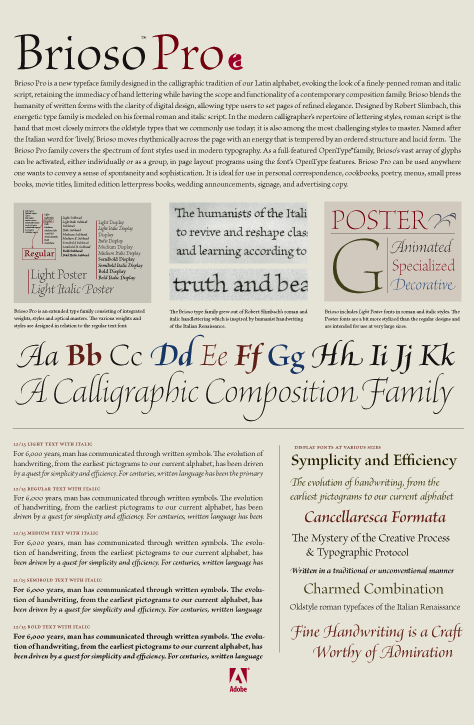
Brioso
Pro |
Robert Slimbach (Illinois, 1956 -)
Este typeface designer, ex-director artístico do Departamento de type design da Adobe, fez poucas criações verdadeiramente originais, mas produziu uma série de famílias de grande sucesso: Adobe Garamond, Myriad, BriosoSlimbach trabalhou na Adobe Systems em San José,
California. Durante a sua actividade na Adobe, Slimbach visitou o
A Brioso Pro é sem dúvida um ponto alto na carreira de Robert Slimbach. Desde que começou «a fazer letras» na década de 1980, Slimbach mostrou forte afinidade com as letras humanistas, caligrafadas ou não; basta ver a Poetica Chancery, a Clafisch Script e a San Vito.
Na Brioso Pro, Bob Slimbach integrou toda a sua perícia e os aprofundados estudos da caligrafia humanista da Renascença italiana (ver exemplo em baixo). Deste esforço resultou uma fonte de nítida inspiração caligráfica. As itálicas (normais e Swash) estão admiravelmente integradas nesta extensa família, apta a satisfazer as exigências de qualquer profissional do desenho gráfico. Faz parte dos requintes da Brioso a escolha entre cinco desenhos, com pesos ópticos decrescentes: Caption, para legendagem; Regular, para texto corrido; Su.head, para subtítulos; o fino Display, para headlines.
Em 1991 recebeu o prestigioso Charles Peignot Award da AtypI por excelência em typeface design.